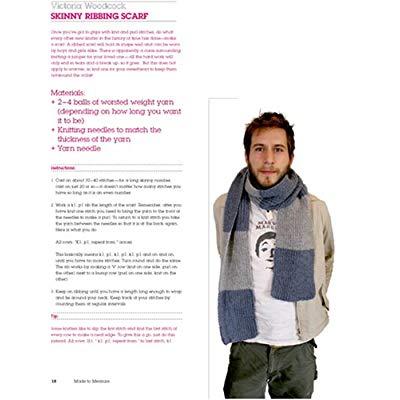
Ich würde gern eine Zeitschrift erstellen und hab im Netz diesen Font gefunden. Könnt ihr mir sagen, welcher das ist? Danke :)!
welche Schrift meinst du denn? ich sehe mindestens zwei verschiedene.
und eine größerer Abbildung wäre nicht schlecht.
Die obere könnte die Rockwell sein
Naja hab das Bild leider auch nicht größer. Ich denke, es ist ein und die selbe Schriftenfamilie.
Junge, Junge, der Typ auf dem Foto hat sich mit seinem Outfit aber von der ein oder anderen Apple-Anzeige inspirieren lassen, oder?
Eigentlich suche ich einfach eine Schrift.. ähnlich wie die Courier. Nur soll sie nicht so weit laufen. Bißchen kompakter das Ganze....!? Im Stil Schreibmaschine, gut lesbar und nicht ewig breit. Was käme denn da noch in Frage?
z.B.
Rockwell
Glypha
Serifa
Suche mal bei myfonts.com nach "slab serif".
Oder soll es tatsächlich schreibmaschinenhafter sein (gleiche Zeichenbreite für alle Buchstaben & Co)?